思源字体系列
思源字体是由 Adobe 在线字体库 Typekityu 与谷歌一起合作开发的,字库对中(简体/繁体)、日、韩三国汉字进行了全面优化支持,可以说是非常全面的,看一下思源黑体、思源宋体:
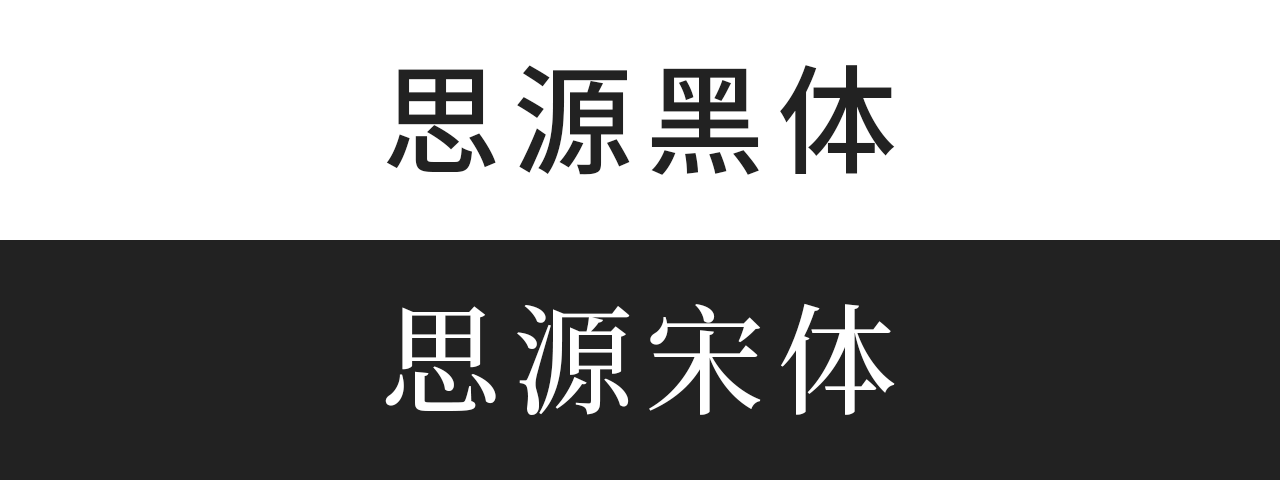
其实思源不仅是个免费字体,还是一个开源字体,任何用户都可以在思源的基础上调整修改出新字体。比如在开源平台 GitHub 上发布的 思源真黑、思源柔黑就是在思源字体的基础上进行调整,虽然名字取的很尬,但是颜值很在线。
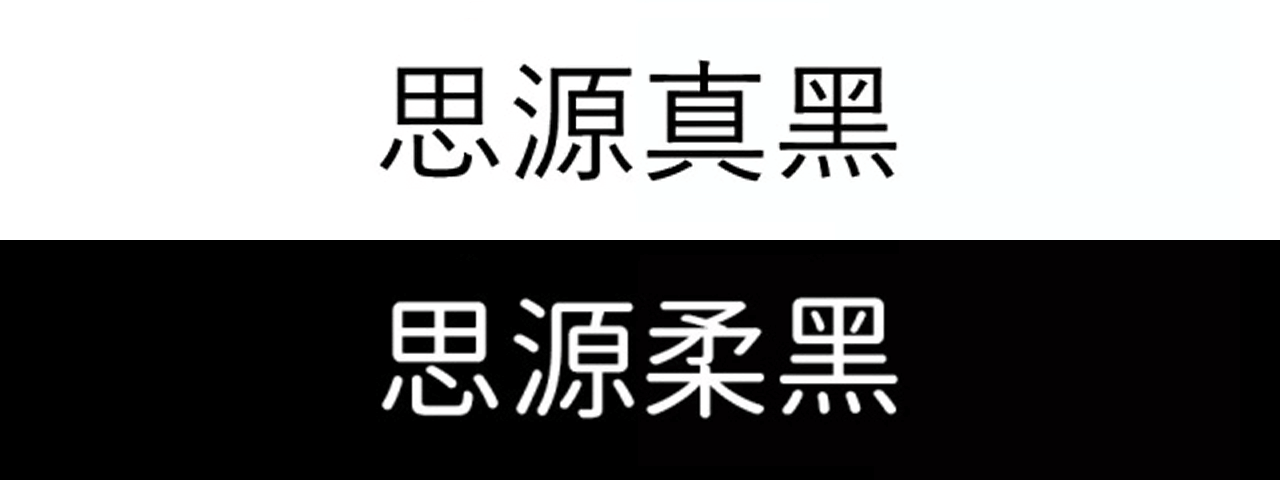
文泉驿字体系列
和思源字体系列一样,文泉驿也是一款开源字库,并且在Linux/Unix系统中获得广泛运用。
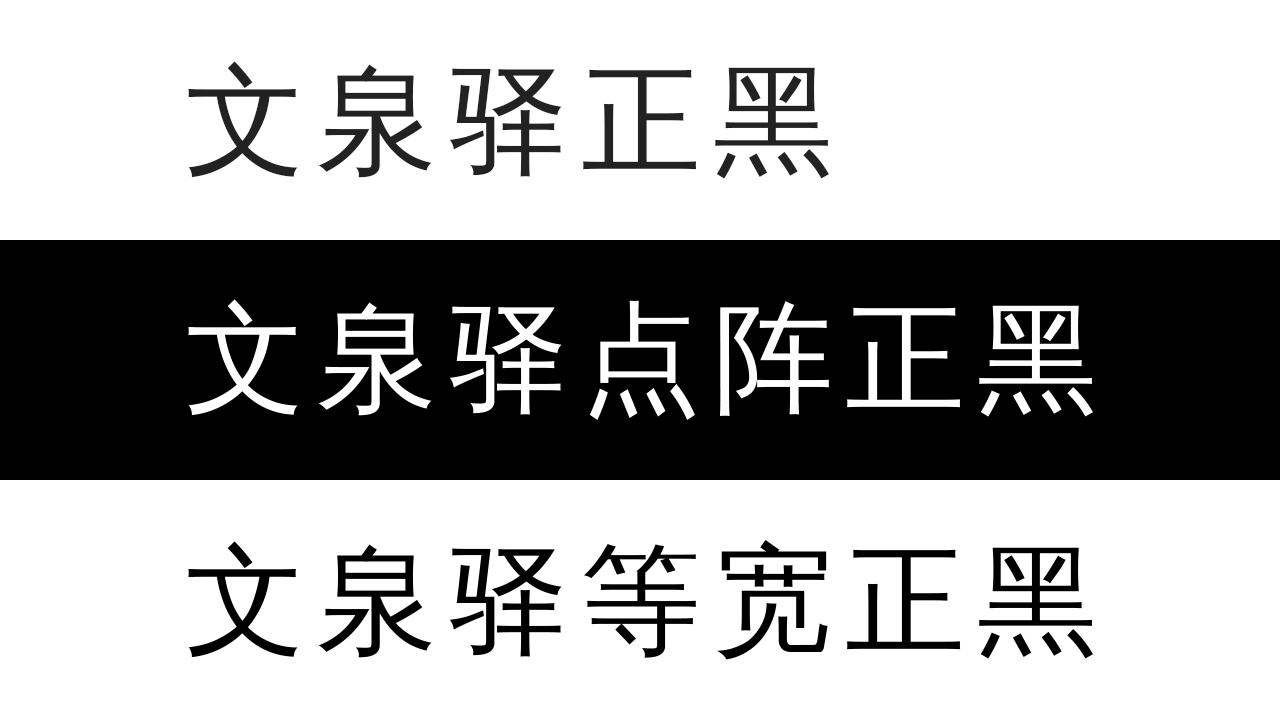
站酷字体系列
站酷不仅是聚集了大量优秀设计师的中国设计师互动平台,同时还分享了多款免费可供商用的字体,其中站酷高端黑就是站酷网近百名设计师参与创作开发的,除此之外,还推出了多款免费字体供大家使用。
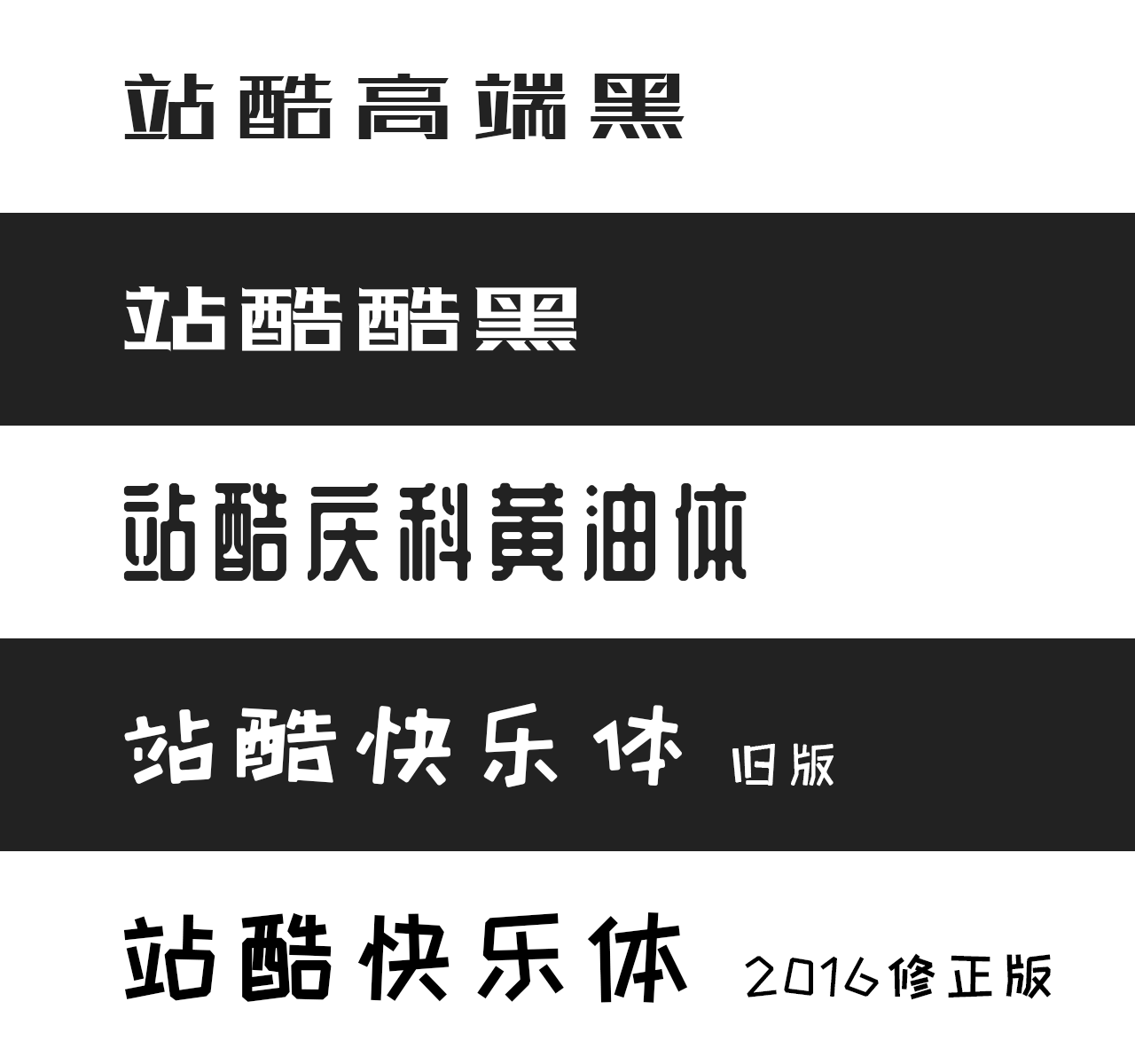
方正字体系列
方正字体是大家接触最多的字体之一,其中有4款是方正字库针对「商业发布」提供的免费字体:方正黑体、方正书宋、方正仿宋和方正楷体,需要注意的是这4款字体虽然可商用,但依然需要方正公司的书面授权。
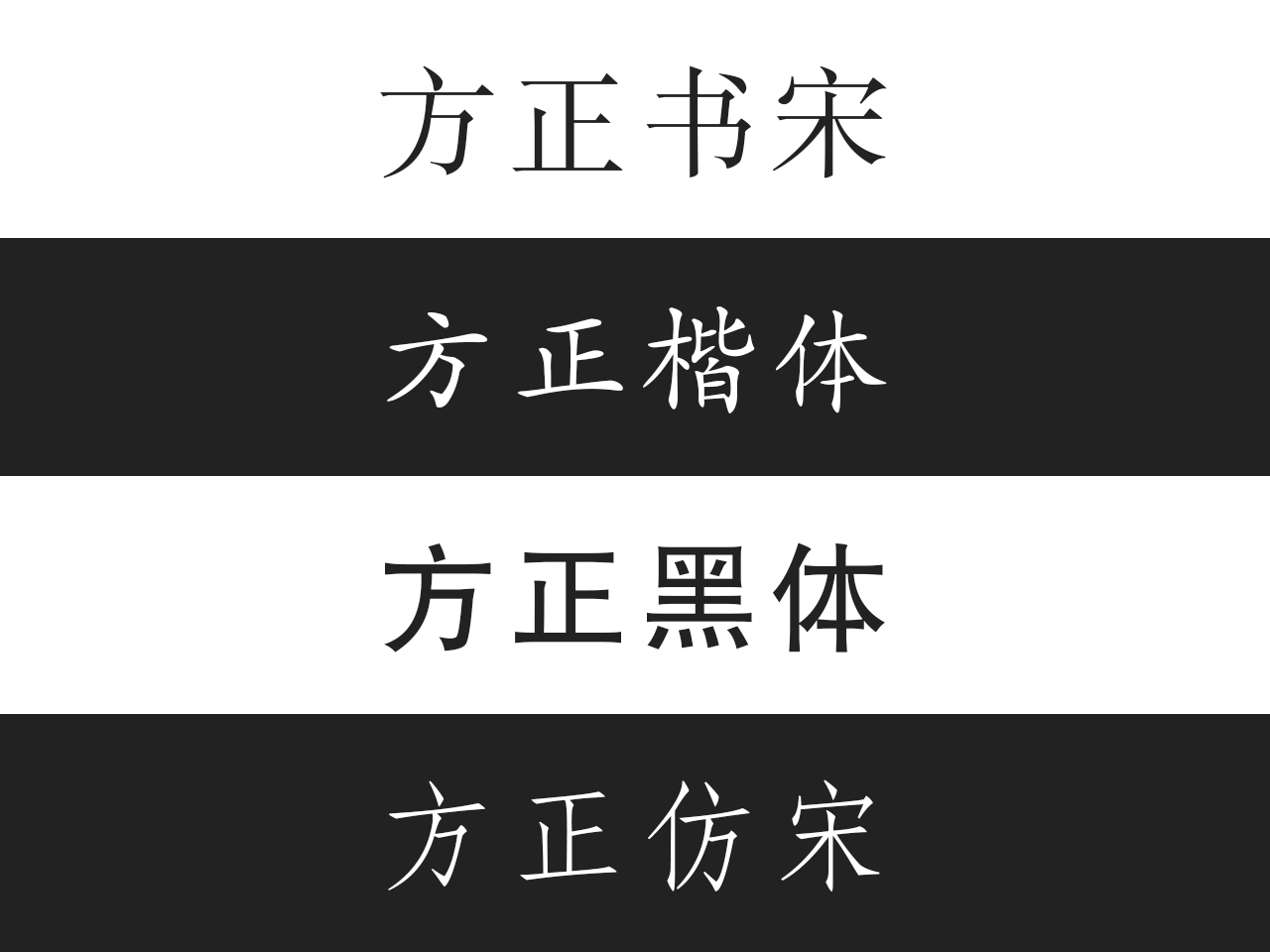
王汉宗字体系列
中原大学数学系王汉宗教授研发,王汉宗教授分别在2000年和2004年先后捐出十套 WCL系列字型和32套新字型,但是由于字形与汉仪字库有大量重复,因此存在各种版权纠纷,这里挑出了几款没有版权纠纷的字体。
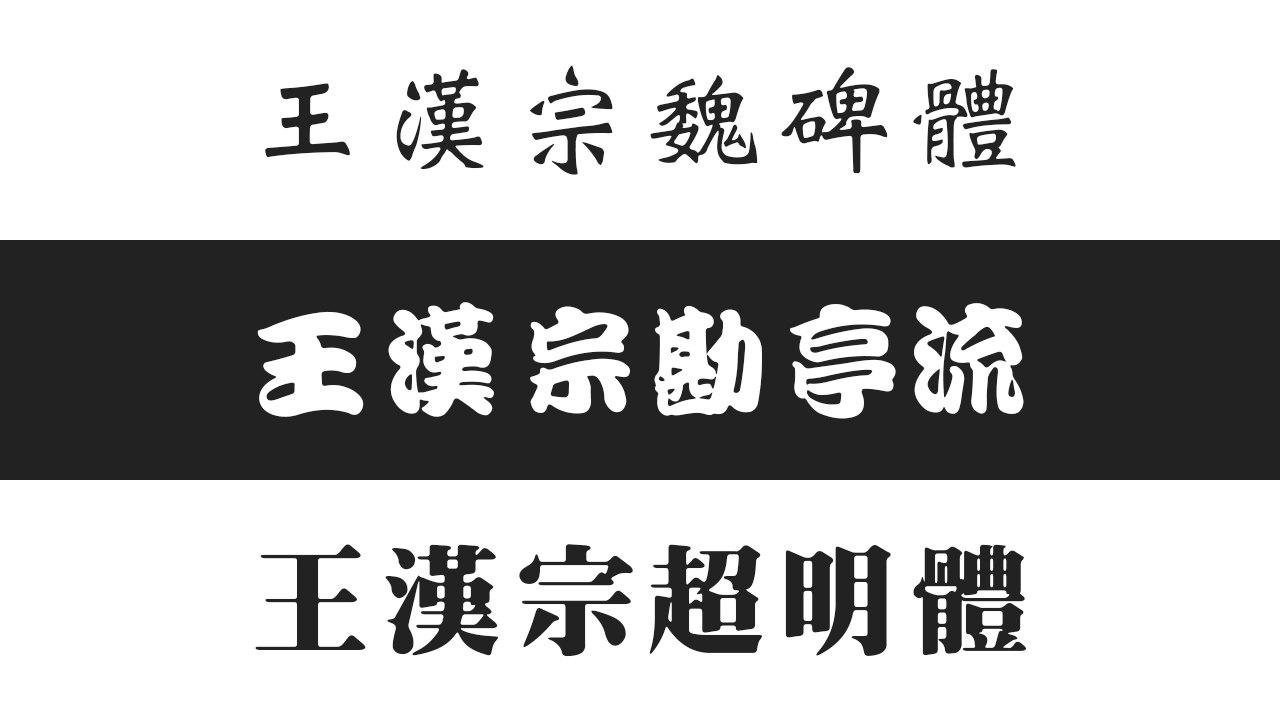
台湾教育部系列
台湾教育部字体系列包含臺灣教育部楷書、臺灣教育部新細明體、臺灣教育部標淮宋體、臺灣教育部國字隸書,这几款字体都是繁体字库,不支持简体字。
其他字体
- 装甲明朝体
日本文字爱好者根据思源宋体调整修改而来,与思源宋体最大的不同在于极细的横线处理,虽然是日本字体,但是完美支持繁体中文。
- Oradano-Mincho名朝体
一个日本铅笔印刷效果字体,颇具古风,同样也是一个完美支持繁体中文的日本字体。
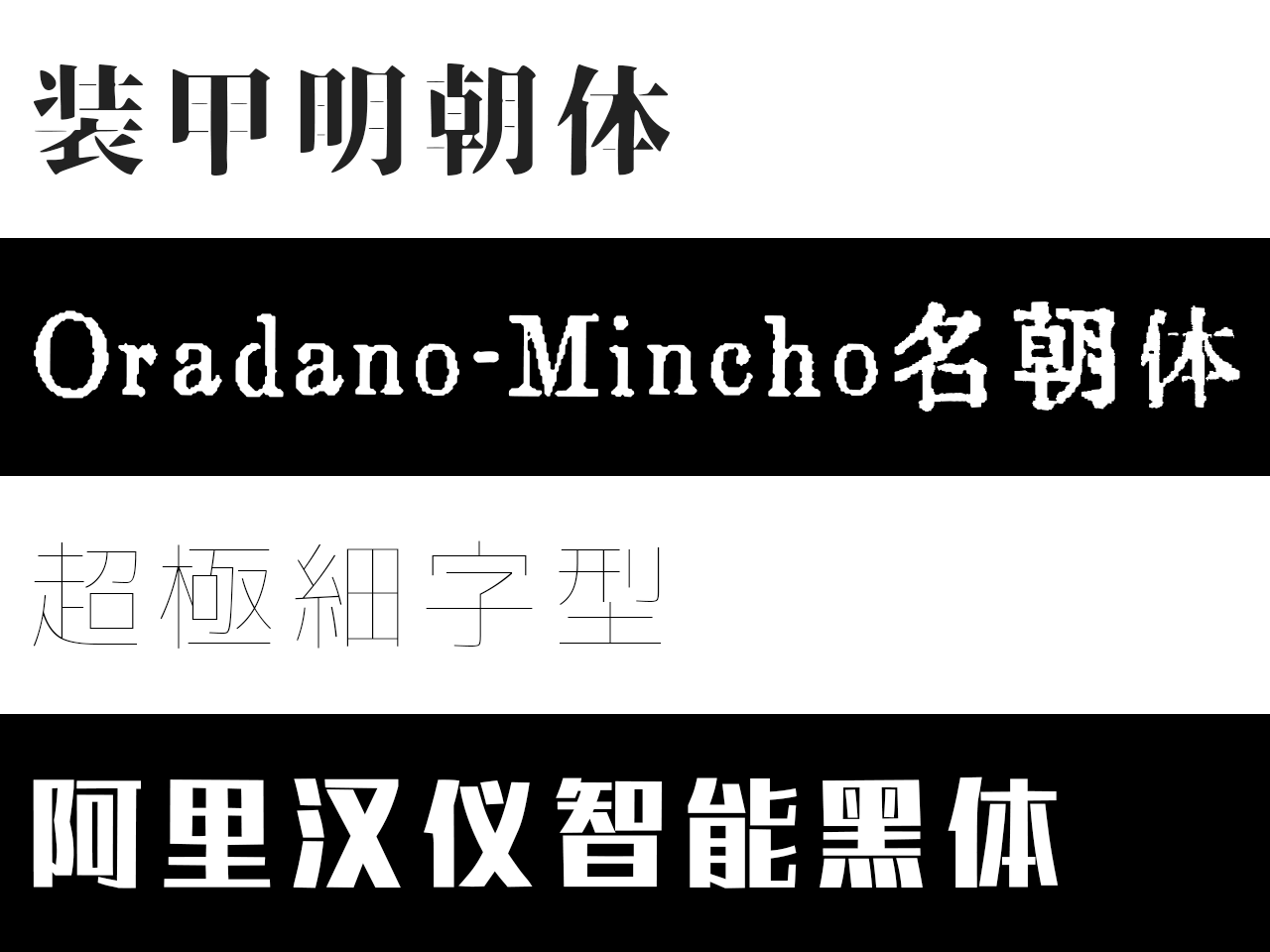
- 超极细字型
这个极细体真的细的很夸张,比平时我们见到的所有细体都还要细。
- 阿里汉仪智能黑体
据说这个字体是阿里巴巴人工智能系统设计,汉仪公司辅助完成的。经过5次迭代最终完成整个字库,实际使用非常适合电商平台。当然,让这个字体仅限阿里巴巴平台上使用。
破产字体-Fandol
为什么要叫它破产字体,因为这个字体的母公司破产了,然后把自己的字体做成免费的……所以请关怀每一个设计公司,很可能下一秒它就随风而去了。